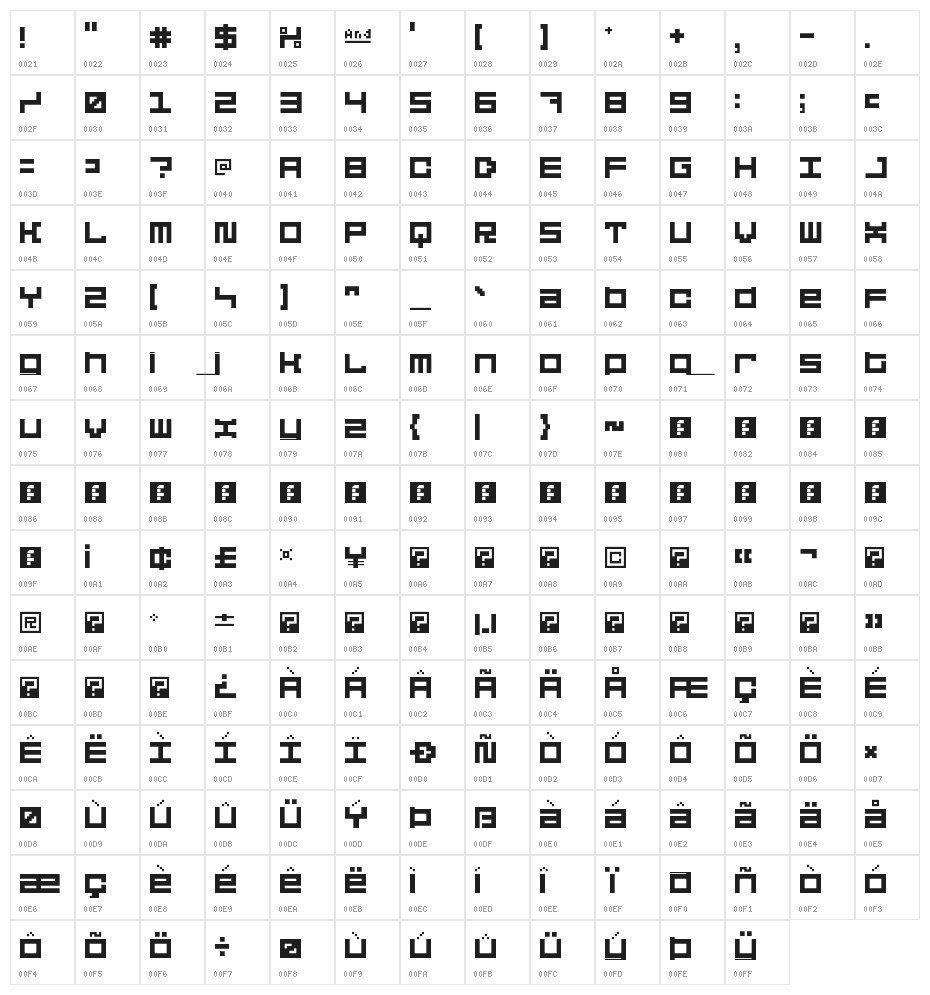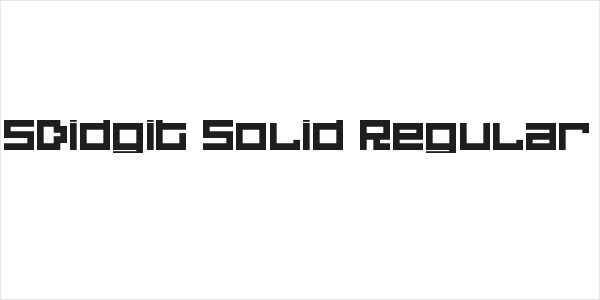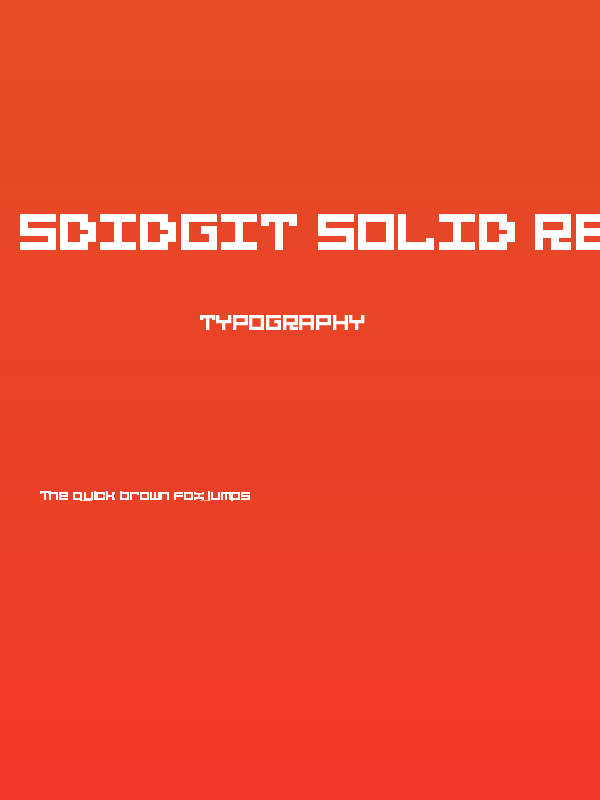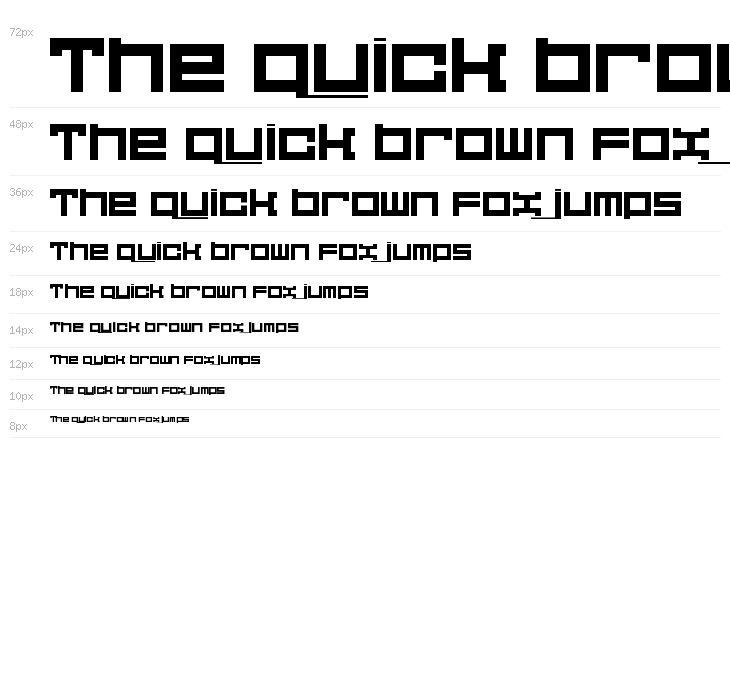
5Didgit Solid Regular Font
| 分类 | Futuristic |
| 整体风格 | Retro, Digital |
| 使用场景 | Headlines, Logos, Digital displays |
| 推荐项目 | Ideal for video game design, tech branding, digital art projects, and retro-themed posters. |